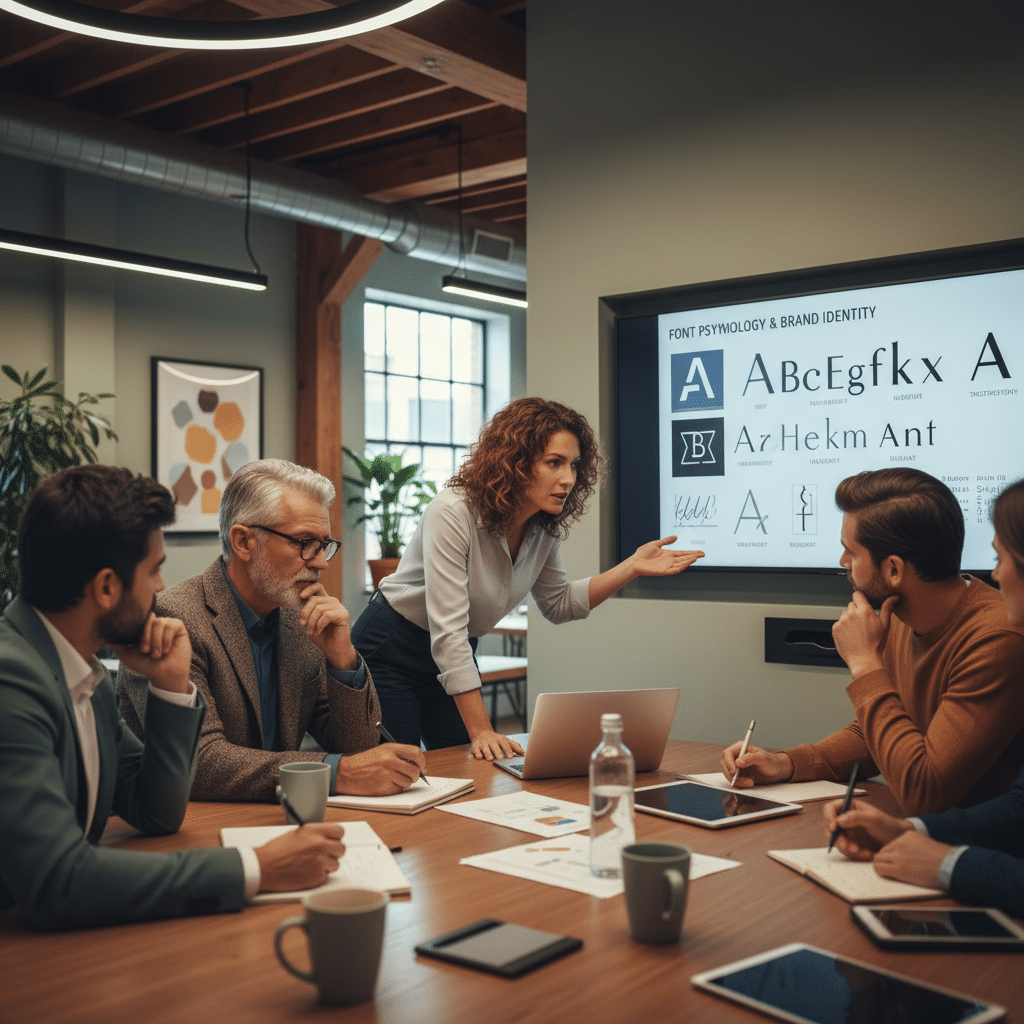
จิตวิทยาฟอนต์: เลือกใช้ยังไงให้แบรนด์ SME น่าจดจำ
การเลือกแบบอักษร หรือ ฟอนต์ (Font) สำหรับแบรนด์ ไม่ได้เป็นเพียงเรื่องของความสวยงาม แต่เป็นเครื่องมือเชิงกลยุทธ์ที่ส่งผลโดยตรงต่อการรับรู้และอารมณ์ของลูกค้า การทำความเข้าใจในศาสตร์แห่งการออกแบบตัวอักษรจึงเป็นสิ่งจำเป็นสำหรับผู้ประกอบการ SME ที่ต้องการสร้างแบรนด์ให้เป็นที่น่าจดจำและสื่อสารตัวตนได้อย่างมีประสิทธิภาพ
ประเด็นสำคัญของการเลือกฟอนต์สำหรับแบรนด์
- การสื่อสารทางอารมณ์: ฟอนต์แต่ละประเภทสามารถกระตุ้นการตอบสนองทางอารมณ์ที่แตกต่างกัน เช่น ความน่าเชื่อถือ ความทันสมัย หรือความหรูหรา
- การควบคุมการรับรู้: การเลือกฟอนต์ที่เหมาะสมช่วยชี้นำการรับรู้ของกลุ่มเป้าหมายที่มีต่อแบรนด์ ทำให้พวกเขามองเห็นภาพลักษณ์ของแบรนด์ตามที่ต้องการ
- การสร้างเอกลักษณ์: ฟอนต์ทำหน้าที่เปรียบเสมือน “เสียง” ของแบรนด์ ช่วยสร้างความแตกต่างและทำให้แบรนด์โดดเด่นเหนือคู่แข่งในตลาด
- ความสม่ำเสมอคือหัวใจ: การใช้ฟอนต์อย่างสม่ำเสมอในทุกสื่อ ไม่ว่าจะเป็นโลโก้ ฉลากสินค้า หรือเว็บไซต์ จะช่วยเสริมสร้างการจดจำแบรนด์ให้แข็งแกร่งยิ่งขึ้น
ความหมายและความสำคัญของจิตวิทยาฟอนต์
การศึกษาเรื่อง จิตวิทยาฟอนต์: เลือกใช้ยังไงให้แบรนด์ SME น่าจดจำ เป็นการสำรวจว่ารูปแบบตัวอักษรส่งผลต่อการรับรู้ อารมณ์ และพฤติกรรมของมนุษย์อย่างไร สำหรับธุรกิจขนาดกลางและขนาดย่อม (SME) การทำความเข้าใจในหลักการนี้ถือเป็นเครื่องมือสำคัญในการสร้างแบรนด์ให้แข็งแกร่ง เมื่อธุรกิจสามารถเลือกใช้ฟอนต์ที่สอดคล้องกับอารมณ์ของกลุ่มเป้าหมายได้ ย่อมส่งผลให้การจดจำแบรนด์ (Brand Recognition) ดีขึ้น และสามารถสื่อสารข้อความที่ต้องการได้อย่างตรงจุดและมีประสิทธิภาพสูงสุด
จิตวิทยาฟอนต์คืออะไร?
จิตวิทยาฟอนต์ (Font Psychology หรือ Typography Psychology) คือการศึกษาว่ารูปทรงและสไตล์ของตัวอักษรมีอิทธิพลต่อวิธีที่ผู้คนรับรู้และตีความข้อมูลอย่างไร โดยธรรมชาติแล้ว สมองของมนุษย์มีความสามารถในการเชื่อมโยงรูปแบบภาพที่มองเห็นเข้ากับความรู้สึกและอารมณ์ที่เกี่ยวข้อง นั่นหมายความว่าการเลือกฟอนต์ส่งผลโดยตรงต่อการรับรู้ภาพลักษณ์ของแบรนด์ นักออกแบบจึงใช้ประโยชน์จากหลักการนี้เพื่อเลือกใช้ฟอนต์อย่างมีกลยุทธ์ในการกระตุ้นความรู้สึกที่เฉพาะเจาะจงในกลุ่มเป้าหมาย เช่น ความไว้วางใจ ความหรูหรา หรือความเป็นมิตร
ฟอนต์ไม่ใช่เพียงแค่ตัวอักษรที่ใช้อ่าน แต่เป็นองค์ประกอบสำคัญของการสื่อสารด้วยภาพที่สามารถบอกเล่าเรื่องราวและบุคลิกของแบรนด์ได้โดยไม่ต้องใช้คำพูด
ทำไมการเลือกฟอนต์จึงส่งผลต่อการรับรู้ของลูกค้า
การเลือกใช้ฟอนต์ที่เหมาะสมมีบทบาทสำคัญต่อธุรกิจ SME ใน 3 ด้านหลัก ดังนี้:
- การสื่อสารทางอารมณ์ (Emotional Communication): จิตวิทยาฟอนต์ช่วยให้สามารถเลือกรูปแบบตัวอักษรที่สอดคล้องกับการตอบสนองทางอารมณ์ที่แบรนด์ต้องการสร้างขึ้น เช่น หากเป็นแบรนด์สินค้าออร์แกนิก อาจเลือกใช้ฟอนต์ที่ให้ความรู้สึกเป็นธรรมชาติและสบายตา
- การควบคุมการรับรู้ (Perception Control): ความเข้าใจในศาสตร์นี้ทำให้นักออกแบบสามารถชี้นำวิธีที่กลุ่มเป้าหมายจะรับรู้และตีความแบรนด์ได้ ตัวอย่างเช่น สถาบันการเงินมักเลือกใช้ฟอนต์ที่ดูมั่นคงและน่าเชื่อถือ เพื่อสร้างความมั่นใจให้กับลูกค้า
- การบรรลุเป้าหมายทางการตลาด (Goal Achievement): การเลือกฟอนต์ที่ถูกต้องจะช่วยสนับสนุนวัตถุประสงค์ของการออกแบบโดยตรง ด้วยการกระตุ้นการตอบสนองทางอารมณ์ที่เหมาะสมซึ่งนำไปสู่การตัดสินใจซื้อของผู้บริโภค
ในทางกลับกัน การเพิกเฉยต่อจิตวิทยาฟอนต์อาจนำไปสู่ความเสี่ยงในการสื่อสารอัตลักษณ์ของแบรนด์ที่ผิดพลาด ทำให้ลูกค้าเข้าใจผิดหรือไม่สามารถเชื่อมโยงกับแบรนด์ได้ ในขณะที่การเลือกฟอนต์อย่างตั้งใจจะสร้างความผูกพันที่แน่นแฟ้นยิ่งขึ้นระหว่างแบรนด์กับกลุ่มเป้าหมาย ซึ่งจะช่วยเพิ่มการจดจำและความภักดีต่อแบรนด์ในระยะยาว
สำรวจประเภทฟอนต์และผลกระทบทางอารมณ์
ฟอนต์สามารถแบ่งออกได้เป็นหลายประเภท แต่ละประเภทมีลักษณะเฉพาะตัวที่ส่งผลต่อจิตวิทยาของผู้รับสารแตกต่างกันไป การทำความเข้าใจคุณลักษณะเหล่านี้จะช่วยให้ผู้ประกอบการ SME สามารถเลือกฟอนต์ที่เหมาะสมกับบุคลิกของแบรนด์ได้อย่างแม่นยำ
| ประเภทฟอนต์ | ลักษณะทางจิตวิทยา | เหมาะสำหรับ |
| ฟอนต์มีเชิง (Serif) | เป็นทางการ, คลาสสิก, สง่างาม, น่าเชื่อถือ, มั่นคง, สื่อถึงประวัติศาสตร์และอำนาจ | แบรนด์หรู, สถาบันการเงิน, สำนักพิมพ์, มหาวิทยาลัย, ธุรกิจที่ต้องการความน่าเชื่อถือสูง |
| ฟอนต์ไม่มีเชิง (Sans-Serif) | ทันสมัย, เรียบง่าย, สะอาดตา, ร่วมสมัย, ตรงไปตรงมา | บริษัทเทคโนโลยี, สตาร์ทอัพ, ธุรกิจสมัยใหม่, แบรนด์ที่เน้นความเรียบง่ายและเข้าถึงง่าย |
ฟอนต์มีเชิง (Serif): ความคลาสสิกที่น่าเชื่อถือ
ฟอนต์ประเภท Serif มีลักษณะเด่นคือมี “เชิง” หรือเส้นขีดเล็กๆ ประดับอยู่ที่ปลายของตัวอักษร ซึ่งเป็นรูปแบบที่พบเห็นได้บ่อยในสื่อสิ่งพิมพ์แบบดั้งเดิม เช่น หนังสือพิมพ์และหนังสือวิชาการ เชิงเหล่านี้ช่วยนำสายตาของผู้อ่าน ทำให้การอ่านข้อความยาวๆ สบายตามากขึ้น ในทางจิตวิทยา ฟอนต์ Serif สื่อถึงความเป็นทางการ, ความมั่นคง, ประวัติศาสตร์ และความน่าเชื่อถือ จึงเหมาะอย่างยิ่งสำหรับแบรนด์ที่ต้องการสร้างภาพลักษณ์ที่ดูภูมิฐานและมีระดับ เช่น แบรนด์แฟชั่นชั้นสูง (Dior), แบรนด์นาฬิกาหรู (Rolex), สถาบันการศึกษา, และสำนักงานกฎหมาย
ฟอนต์ไม่มีเชิง (Sans-Serif): ความทันสมัยและเรียบง่าย
คำว่า “Sans” ในภาษาฝรั่งเศสแปลว่า “ปราศจาก” ดังนั้น ฟอนต์ Sans-Serif จึงหมายถึงฟอนต์ที่ไม่มีเชิงประดับที่ปลายอักษร ทำให้มีรูปลักษณ์ที่ดูสะอาดตา เรียบง่าย และทันสมัย ฟอนต์ประเภทนี้ได้รับความนิยมอย่างสูงในยุคดิจิทัล เนื่องจากอ่านง่ายบนหน้าจอที่มีความละเอียดแตกต่างกัน ในเชิงจิตวิทยา ฟอนต์ Sans-Serif สื่อถึงความร่วมสมัย, ความตรงไปตรงมา, นวัตกรรม และความเป็นมิตร จึงเป็นตัวเลือกที่ยอดเยี่ยมสำหรับบริษัทเทคโนโลยี, สตาร์ทอัพ, ธุรกิจบริการสมัยใหม่ และแบรนด์ที่ต้องการสื่อสารกับคนรุ่นใหม่ด้วยภาพลักษณ์ที่เข้าถึงง่ายและไม่ซับซ้อน